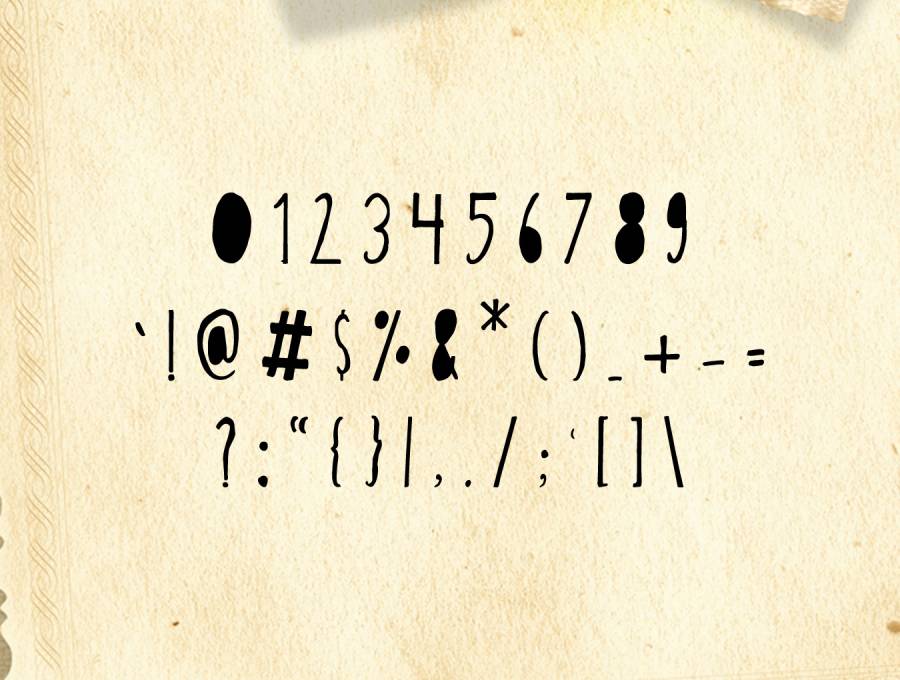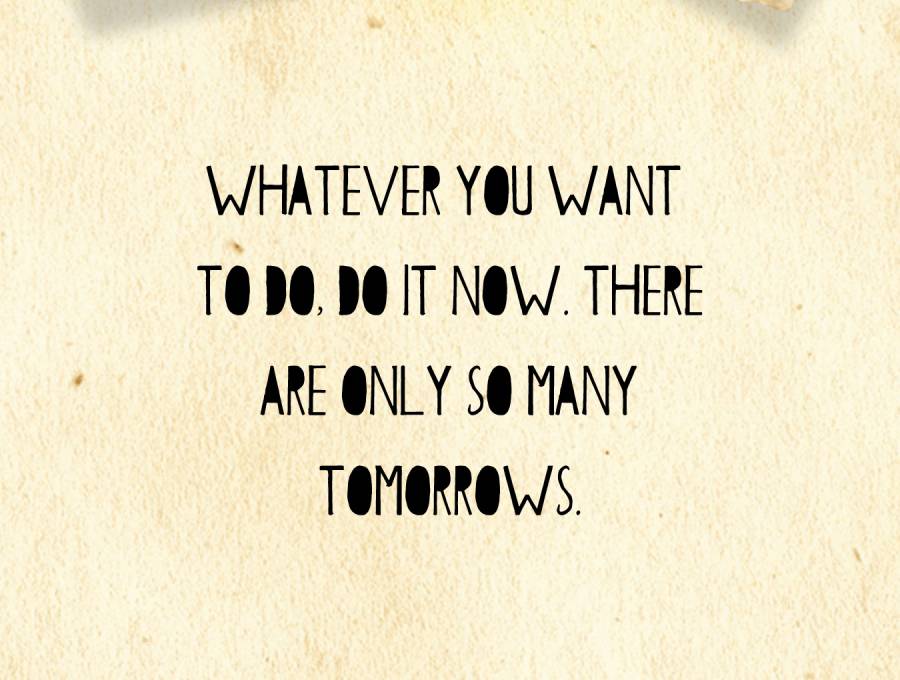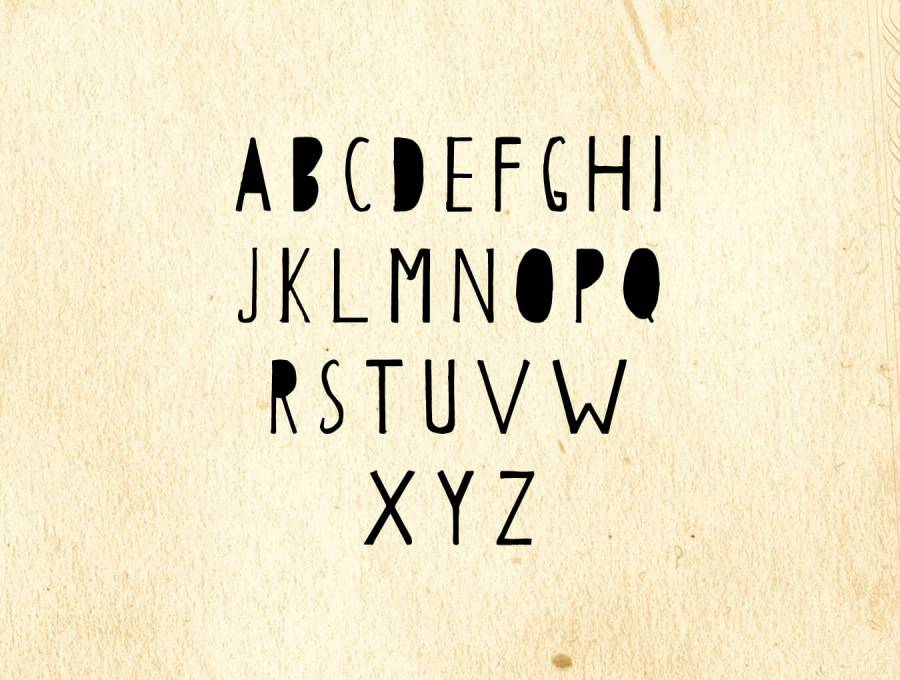
Papercutting 2字体系列包,剪纸字体
Papercutting 2 Font Family Pack, Papercutting Fonts
我们为您呈现Papercutting,这是一种有两种风格的手写字体;常规和轮廓字体。 100%手工绘制。字体完美地捕捉了剪纸相关工艺的结构,适合您作品的装饰。